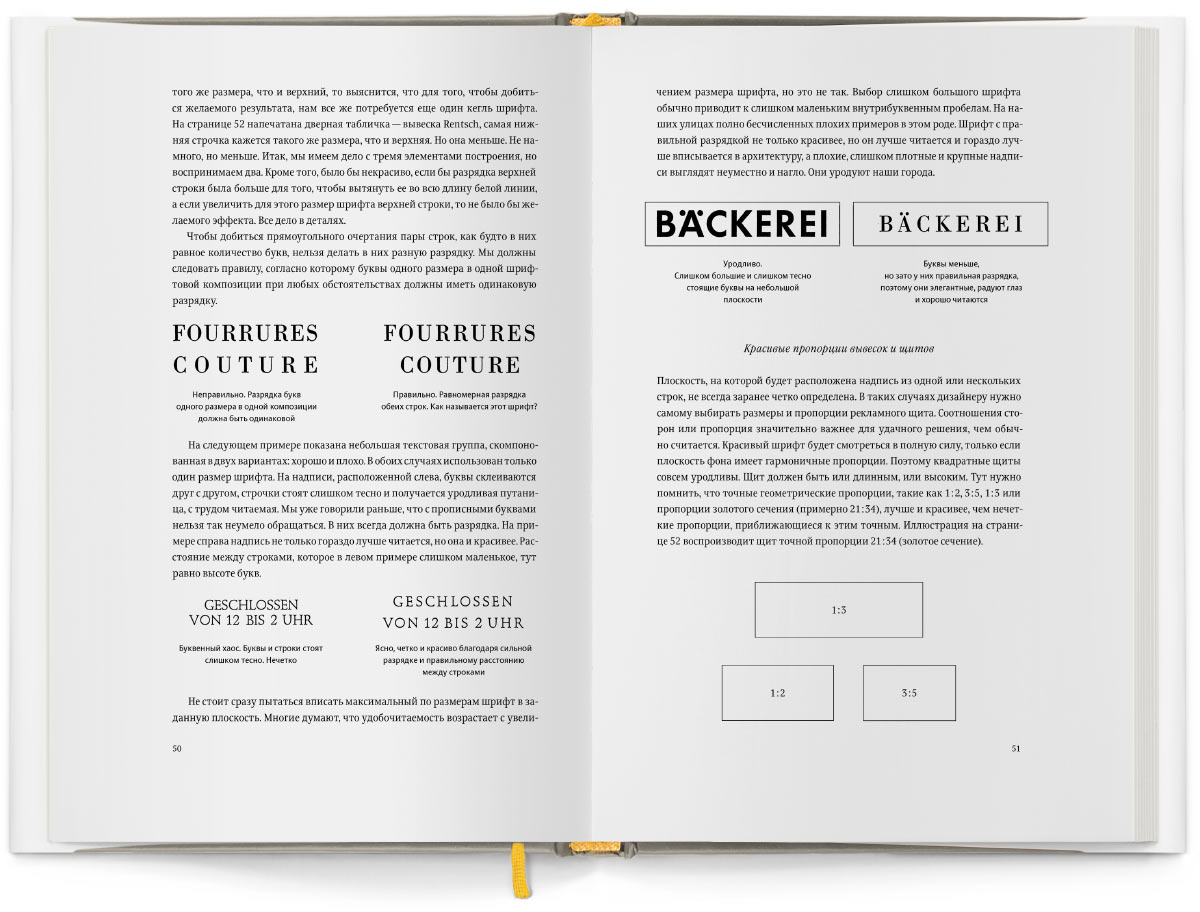
Книга Яна Чихольда Образцы шрифтов
Автор: Ян Чихольд
«Образцы шрифтов» — сборник прекрасных шрифтовых примеров, составленный Яном Чихольдом, известным типографом и художником книги. В издание попали шрифты исключительной красоты, находящиеся вне времени и моды, — настоящие образцы для подражания в шрифтовом дизайне.
Прежде чем представить коллекцию образцов, Чихольд скрупулезно анализирует форму и устройство букв, разбирает плохие и хорошие шрифты, пишет об использовании прописных и строчных знаков, межбуквенном и междустрочном расстояниях. Много внимания уделено правильному подбору шрифта к задаче, шрифтовым композициям и типографике в городской среде. Многие ценные исторические иллюстрации приведены в реальном размере и тщательно отретушированы автором, поэтому выглядят лучше, чем в плохо сохранившихся оригиналах.![]()
«Эта книга, являющаяся результатом многолетнего изучения шрифтовых форм, будет долго служить источником материала для шрифтовиков, графиков, литографов и художников других смежных областей. Отобранные для нее шрифты отвечают самым строгим критериям, поэтому хочется надеяться, что они выдержат суд грядущих десятилетий. В альбоме есть шрифты знаменитые и неизвестные, готовые для немедленного использования и те, что служат для вдохновения, шрифты для школяров и для мастеров. Они должны помочь развитию настоящей культуры шрифтов и их применения.»
Из предисловия автора
Ян Чихольд (1902–1974) — немецкий типограф, дизайнер и преподаватель, внесший значительный вклад в развитие графического и книжного дизайна, а также типографики XX века. За свою долгую карьеру Чихольд оформил огромное количество швейцарских и английских изданий, написал несколько книг, которые остаются актуальными и востребованными у современных графических дизайнеров и художников книги, посвятил много времени изучению шрифтов и работе с ними.
За заслуги в развитии типографского искусства награжден золотой медалью Американского института графических искусств в Нью-Йорке (высшая награда полиграфической промышленности США), возведен в ранг почетного королевского дизайнера Королевским обществом искусств в Англии, избран членом-корреспондентом Немецкой академии искусств в Берлине, получил премию Гуттенберга (высшая европейская награда за заслуги в области типографского искусства).